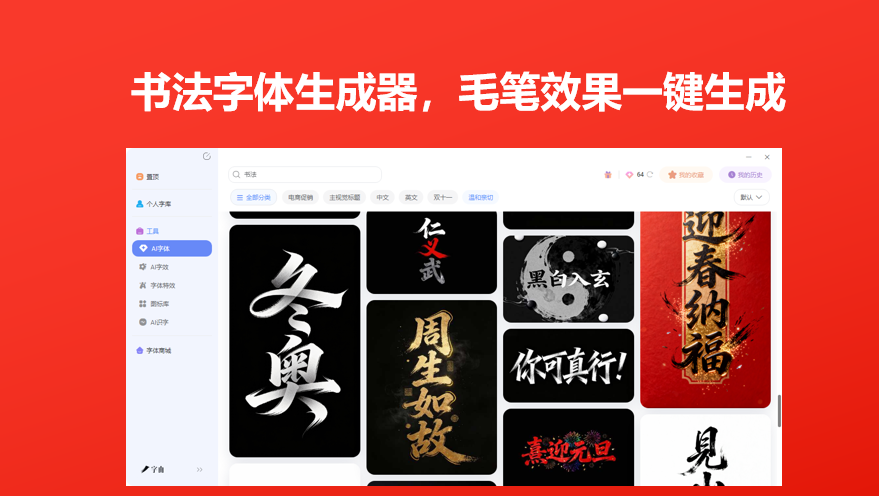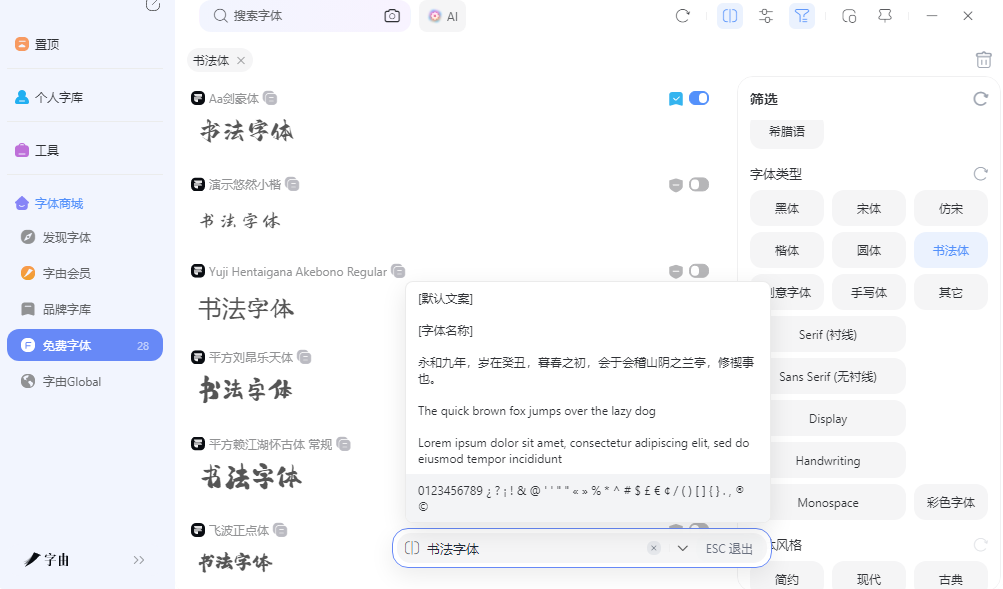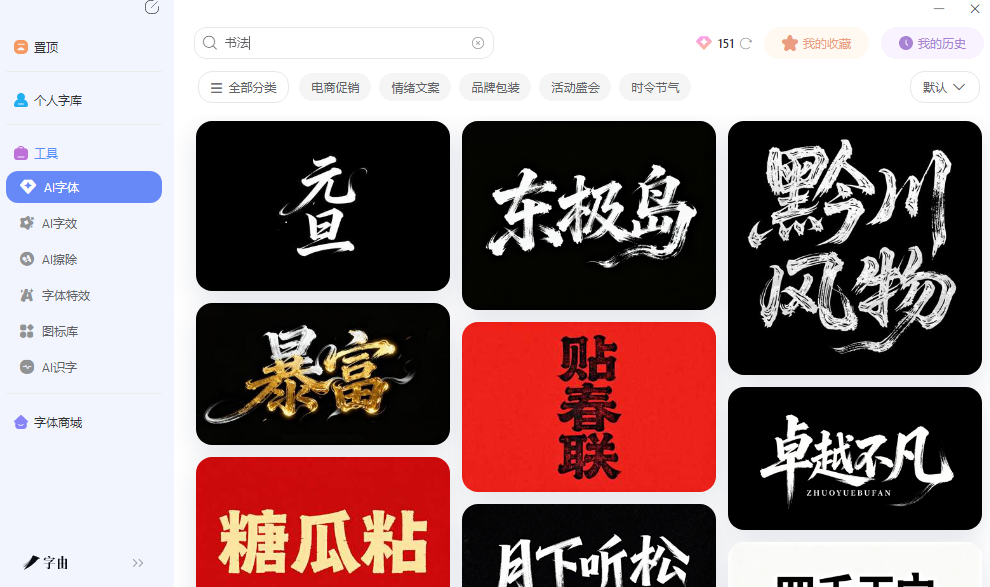
做中式风格的设计,书法字往往是点睛之笔。海报上的大标题用行书显得洒脱,品牌标语用楷书显得稳重,文创包装用隶书显得古朴。但很多人不会写毛笔字,找书法字体文件又担心字符集不全,装完后发现缺字缺得厉害。其实现在有不少工具可以直接生成带毛笔效果的艺术字图片,输入文案就能拿到成品,不需要自己动笔也不需要安装字体文件。这篇文章整理的五个平台,帮你把书法字这件事变得简单一些。
字由字体库里书法体是单独分类的,和手写体区分开来,书法体偏向传统书体的数字化再现,行书、楷书、隶书、草书都有覆盖。找的时候先点书法体分类,再勾选免费商用标签,结果列表里就是全部允许商业使用的书法资源,不需要逐个翻详情页确认授权。
预览框对书法体尤其重要。同样的书法字体,输入"春风得意"和输入"科技未来",气质可能完全不同。有些书法体适合诗词歌赋的优雅语境,有些则适合品牌标语的现代排版。字由的预览支持输入自己的文案,调整字号后观察笔画在不同大小下的清晰度,有些字体放大后飞白效果很明显,有些则显得单薄。确认效果后再激活,避免了装完发现不合适再卸载的反复操作。
对于需要书法效果但不是字体文件本身的场景,字由的AI字体功能可以直接生成带特效的书法字图片。模板库里有不少书法风格的特效模板,水墨渲染、鎏金质感、毛笔飞白等方向都有覆盖。选一个模板,把自己的文案替换进去,大约二十多秒生成一张透明背景的PNG图片,可以直接拖进海报或者电商详情页里做标题。这种方式比找书法体再自己调效果要快不少,尤其适合时间紧、需要快速出方案的情况。
字体转换网是一个字体格式转换和书法字体生成的综合平台。除了支持把文字转换为书法字体外,还提供了字体文件格式转换功能,比如TTF转OTF、字体压缩包处理等。对于从各处下载了书法字体文件、但格式不统一的用户来说,这个工具比较实用。
书法字体生成方面,网站上提供了多种毛笔字体风格,输入文案后选择风格即可生成。作为书法字体生成器的渠道,字体转换网的优势在于功能综合性强,既能生成书法字图片,又能处理字体文件格式,适合需要同时解决生成和格式问题的用户。操作流程简洁,生成速度较快,对临时需要书法效果的用户来说足够用了。
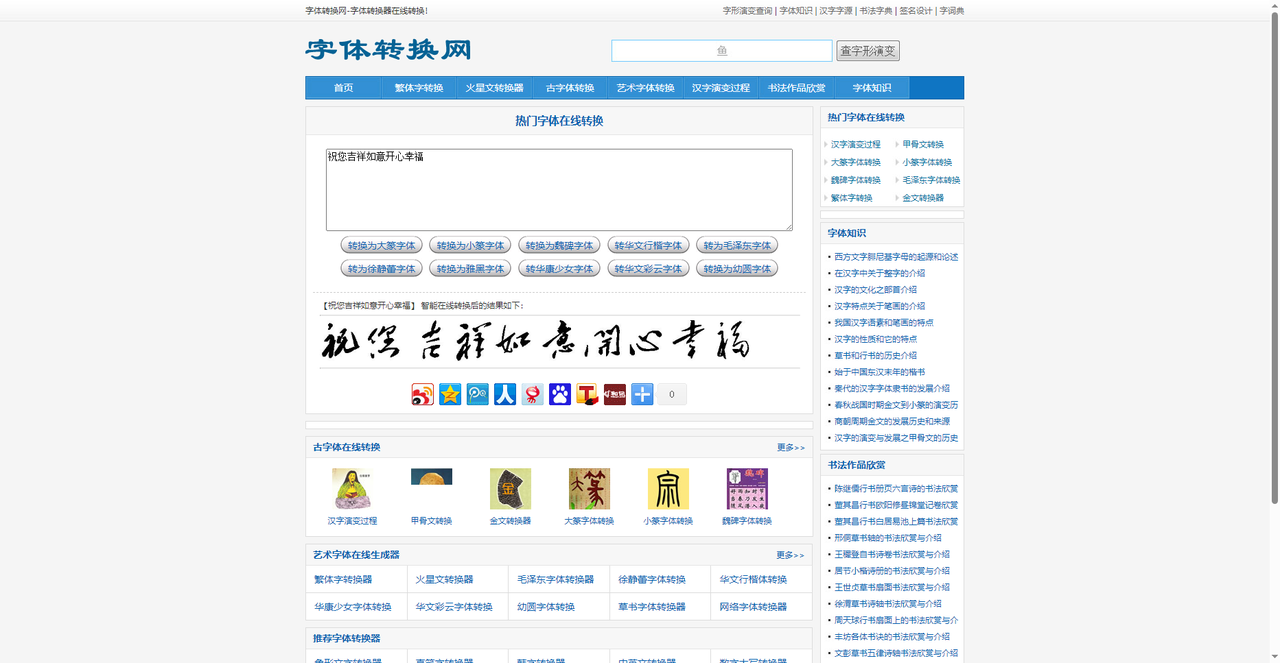
书法艺术字体在线生成器是一个专注书法风格转换的工具,提供了多种艺术化的书法效果。除了传统的行书、楷书外,还有一些创意化的书法变体,比如立体书法、描边书法、渐变书法等。用户输入文字后选择效果类型,系统会生成一张带艺术处理的书法字图片。
这个工具对想要书法效果但又希望有一些现代感的用户比较实用。传统书法体有时候显得过于古典,不太适合现代商业项目,而这个平台上的创意变体在保留书法韵味的同时增加了一些设计感。作为书法字体生成器的补充渠道,它的优势在于风格多样化,既有传统也有创新,适合需要差异化视觉效果的项目。生成的图片可以直接下载,流程顺畅。
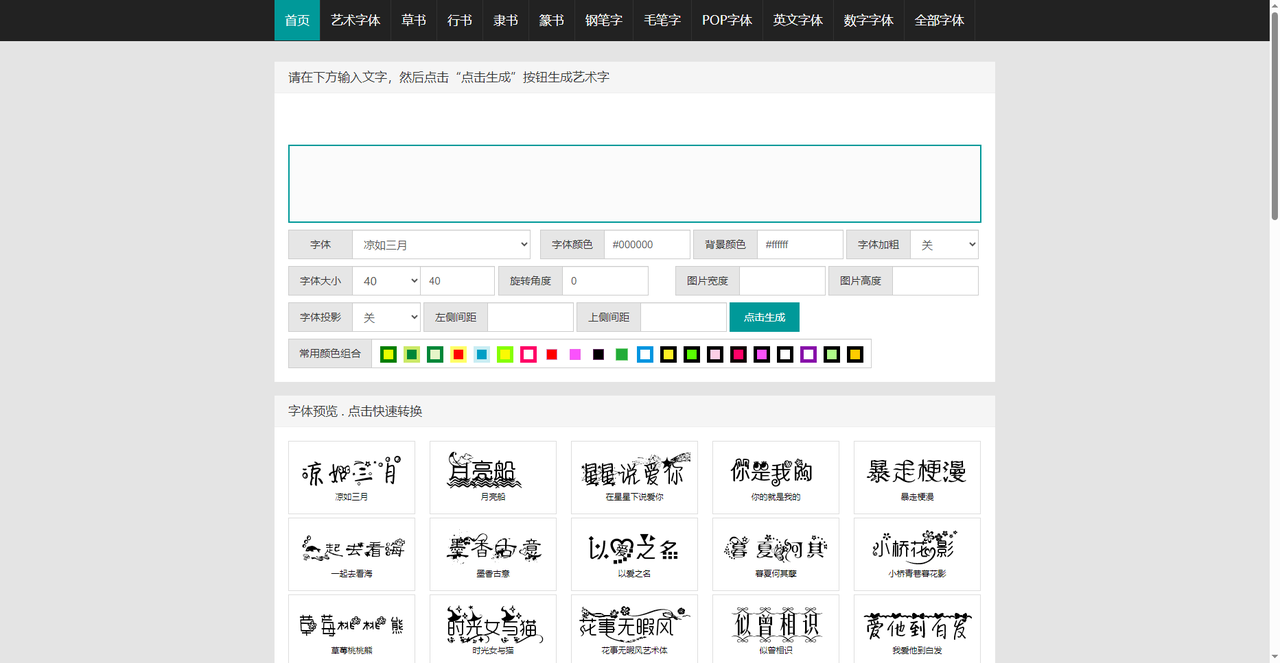
第一字体网是一个在线字体转换平台,支持把输入的文字转换为多种书法字体风格。网站上提供了行书、楷书、隶书、草书等多种书体选择,用户输入文案后选择喜欢的书体,系统会生成对应的书法字图片。
这个工具对需要快速获得书法效果的用户比较友好。操作流程简洁,输入文字、选择书体、生成图片,三步完成。生成的图片可以直接下载使用,也可以复制到剪贴板粘贴到其他地方。作为书法字体生成器的渠道,第一字体网的优势在于书体分类比较传统,覆盖了主流书法类型,适合需要正统书法风格的场景。网站上还提供了字体大小和颜色调节选项,可以微调效果以匹配具体需求。
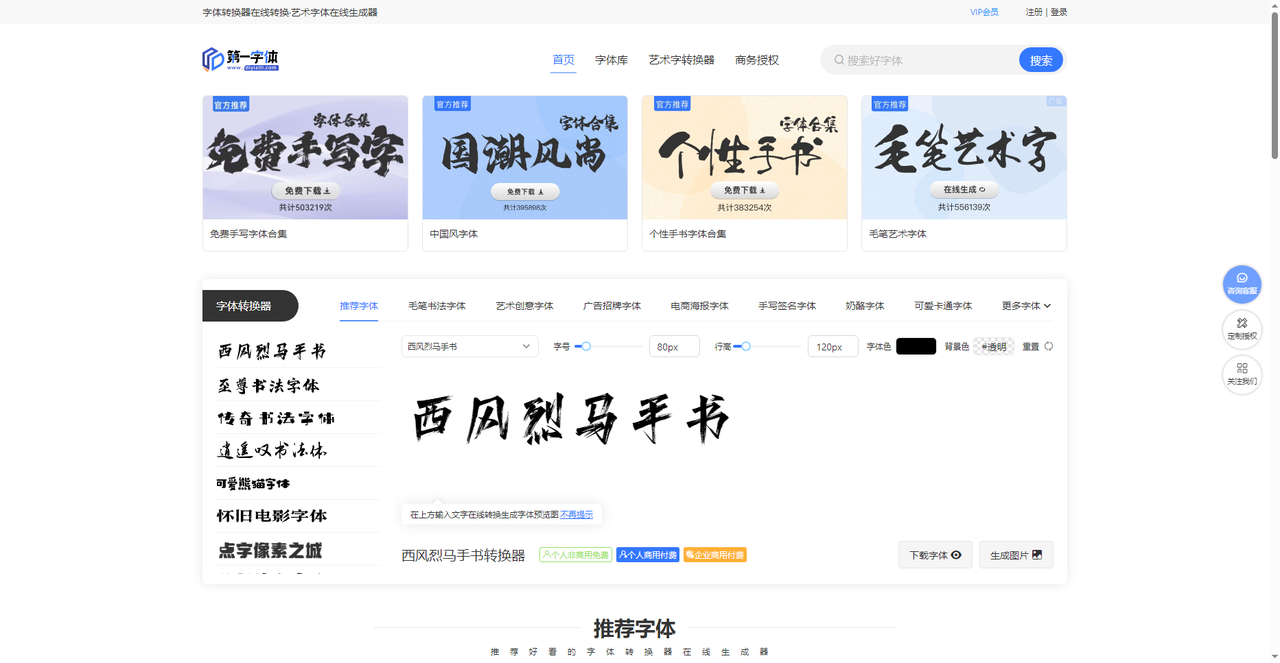
以观书法网是一个专注书法学习和临摹的平台,核心功能是展示历代名家碑帖的高清图片。网站上收录了大量经典碑帖,包括王羲之、颜真卿、柳公权等名家的代表作,每幅碑帖都支持高清放大查看笔画细节。
对于需要书法字体生成器的用户来说,这个平台的实用价值在于可以直接从碑帖中找到想要的字形。输入一个汉字,系统会在碑帖库中搜索对应的写法,展示出不同名家对这个字的处理方式。想做"龙"字的标题,可以看到王羲之的行书、颜真卿的楷书、怀素的草书分别是怎么写的,选择最接近项目气质的那一款。作为书法字体生成器的辅助渠道,以观书法网在字形的权威性和多样性方面比较突出,适合对书法品质有较高要求的项目。
想做中式风格但自己不会写毛笔字,字由的书法体分类配合AI字体生成,从找字体到出图非常流畅,作为书法字体生成器的主力渠道效率不错。以观书法网的碑帖库适合对字形权威性有要求的项目。第一字体网的传统书体覆盖比较全。书法艺术字体在线生成器的创意变体适合现代商业场景。字体转换网则在格式处理方面有额外功能。